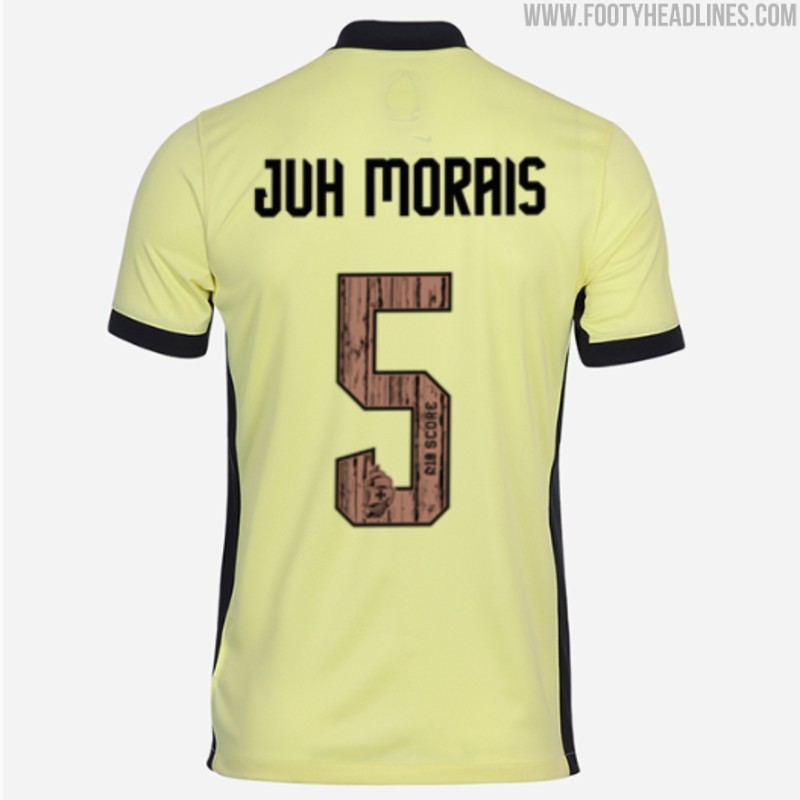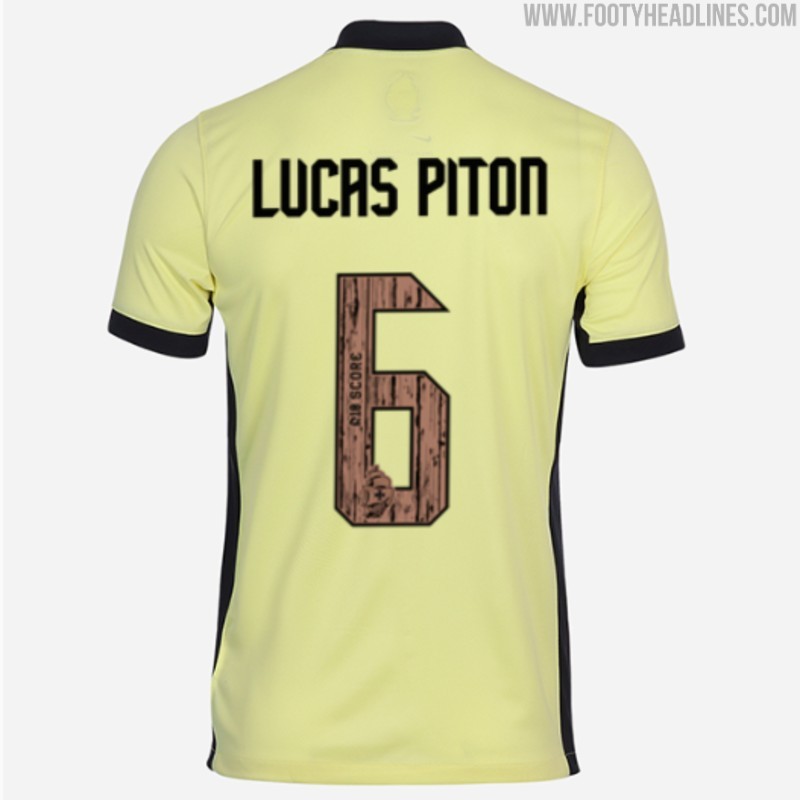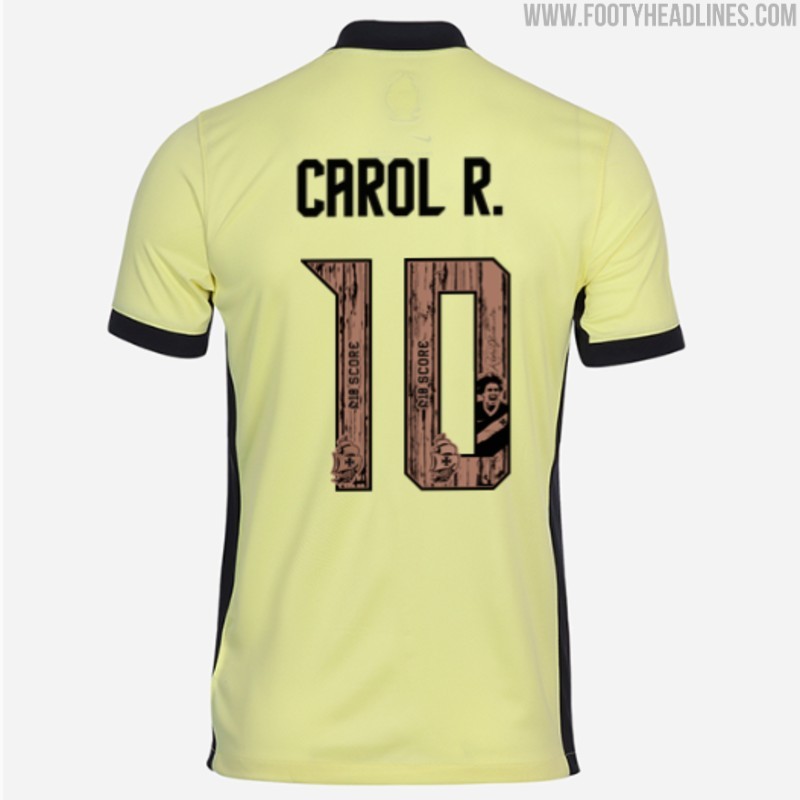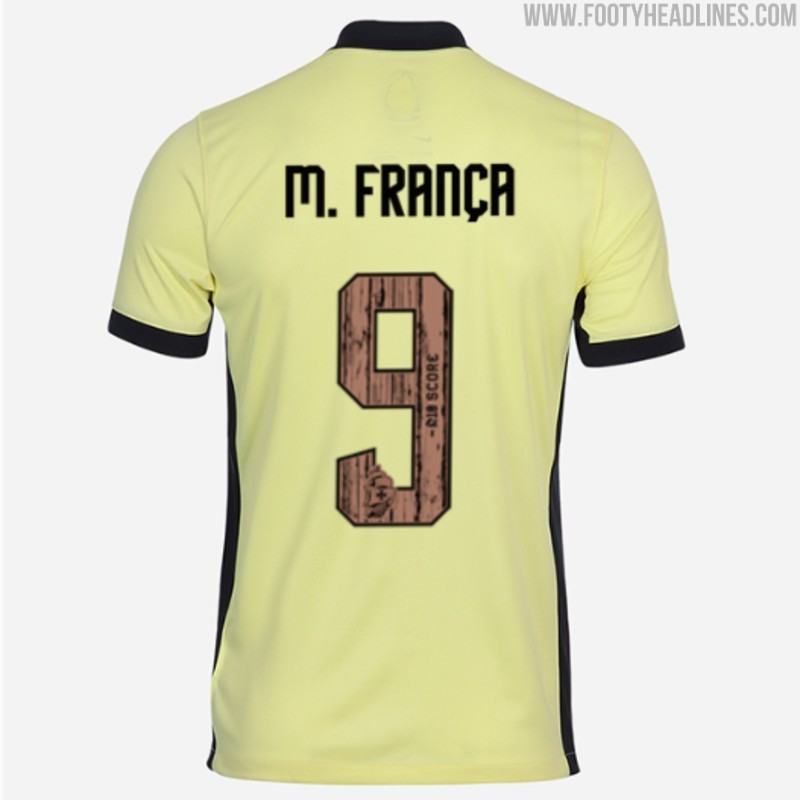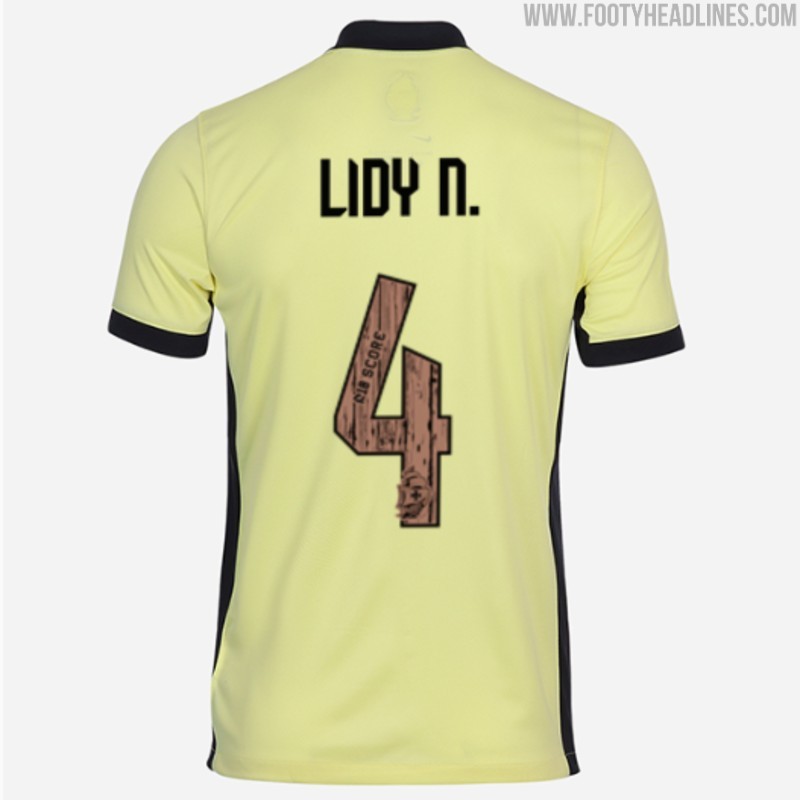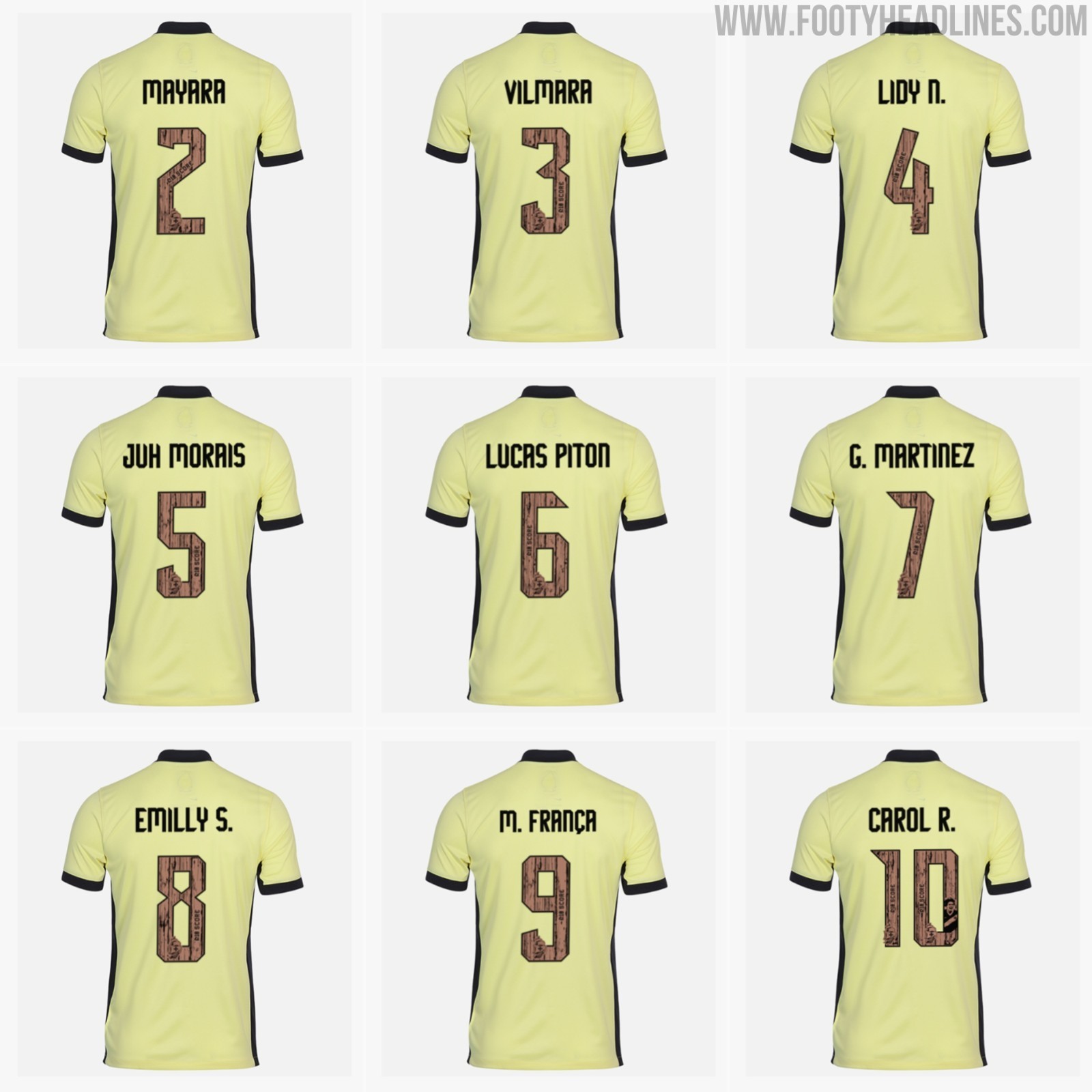
La tercera camiseta de Nike para el Vasco da Gama 26-27 presenta una tipografía con vetas de madera
• Presentación de la Camiseta: Nike ha lanzado la tercera camiseta del Vasco da Gama para la temporada 26-27, destacando un detalle de personalización único.
• Tipografía con Vetas de Madera: La tipografía de los números de esta camiseta presenta una distintiva textura de vetas de madera en tonos marrones.
• Homenaje a la Exploración Marítima: El diseño de la tipografía con textura de madera rinde homenaje a los cascos de los históricos barcos portugueses, en línea con el concepto de exploración marítima de la camiseta.
La nueva tercera camiseta del Vasco da Gama para la temporada 26-27 incluye un detalle de personalización único.
La tercera camiseta de Nike para el Vasco da Gama 26-27 presenta una tipografía con vetas de madera
Tipografía de la tercera camiseta del Vasco da Gama 26-27
Los números de la tercera camiseta del Vasco 26-27 presentan una distintiva textura de vetas de madera en tonos marrones. Diseñados por Nike para completar el concepto de exploración marítima de la camiseta —que combina una base amarilla pálida que recuerda a las velas envejecidas con un gráfico de una carabela en el interior del cuello—, la tipografía con textura de madera rinde homenaje a los cascos de madera de los históricos barcos portugueses.